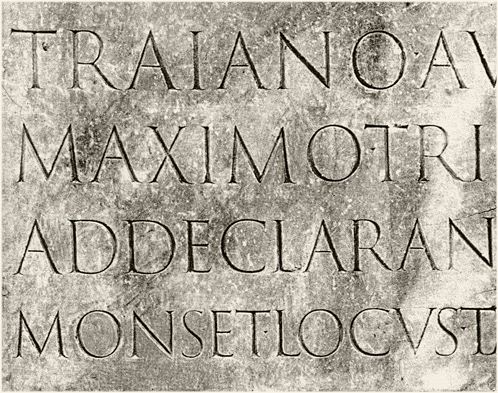
Capitalis Monumentalis
Kurze Frage an die Experten: Ist die Trajan die ultimative digitale Umsetzung der Capitalis Monumentalis (Anhang: Trajanssäule) oder gibts dazu noch andere Geheimtipps?